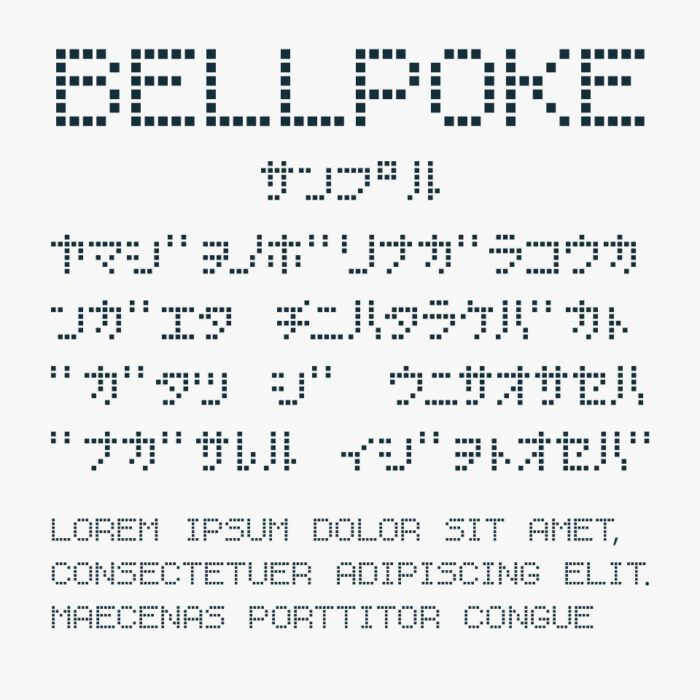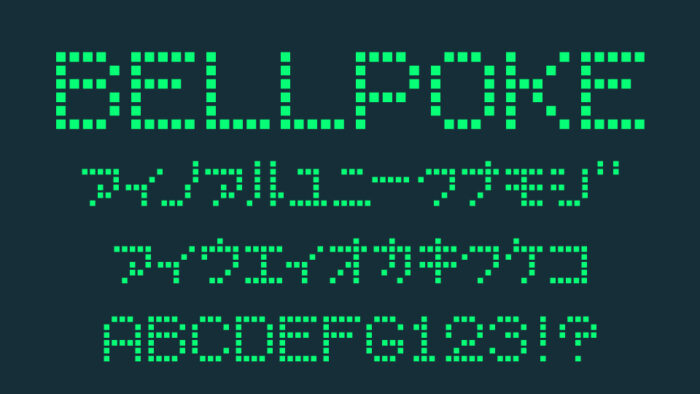
BELLPOKEフォントは、ポケベルの文字表示を思わせるドット表現がとても可愛いなドットフォントです。
ひと文字ごとが正方形ドットで構成されていて、レトロデジタルな印象がありつつも、遊び心たっぷりなデザインがとてもステキです。
ポケベルのようなレトロでどこか懐かしく、ノスタルジックな空気のあるので90年代感やレトロゲームなどにもぴったりなフォントです。
収録文字は、半角カタカナ・アルファベット(大文字)・数字・記号が収録されています。(カタカナは、半角カタカナに対応しているフォントとなるので、変換にご留意ください。)